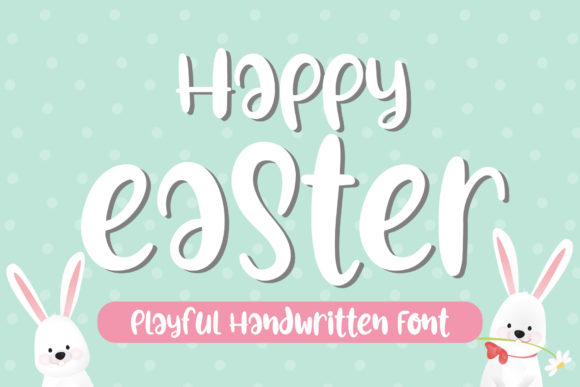
Happy Easter
Mencari elemen desain yang tepat bisa jadi sulit, namun Happy Easter menawarkan koleksi luar biasa yang akan langsung meningkatkan kualitas karya Anda.
Baik Anda membuat produk POD (Print on Demand), undangan pernikahan, atau grafis media sosial, Happy Easter adalah pilihan yang sangat ideal.